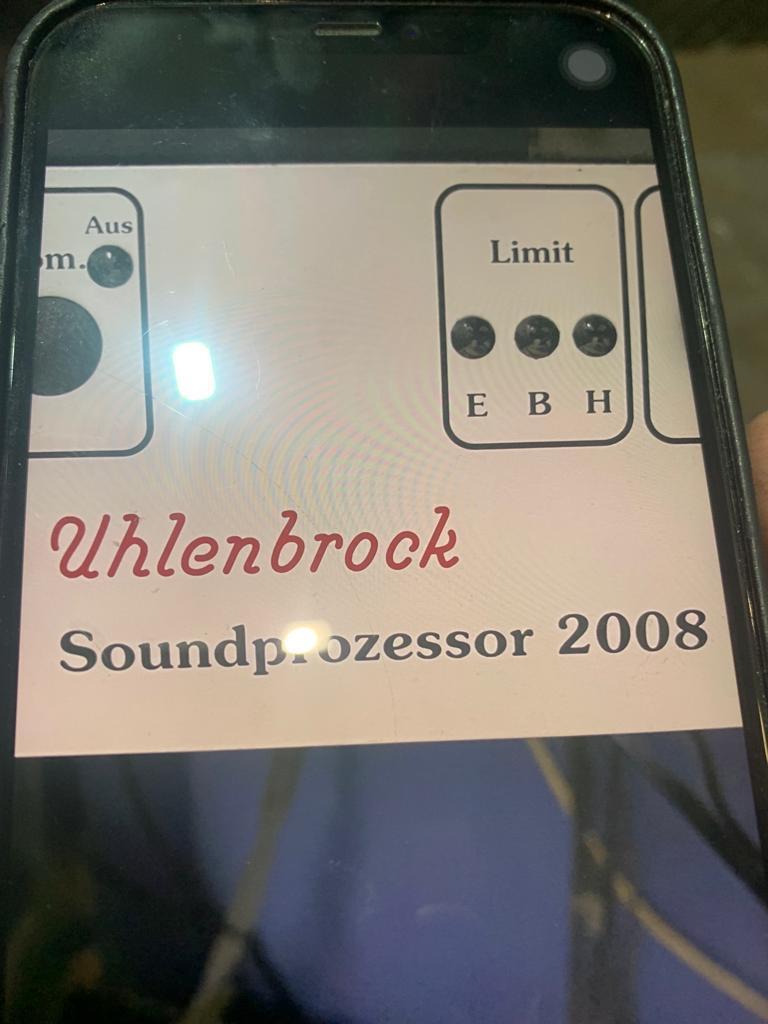
Suche die Schrift von einem Fahrgeschäft (BreakDancer)
ich soll die Frontplatte eines BreakDancers aufarbeiten und kann die Schrift von "Uhlenbrock" nirgends finden.
Ich kann nur vermuten, dass das ganze ca. 2008 entstanden ist.
Ist es überhaupt ein Font oder wurde das damals nur digitalisiert.
Das sieht so aus, als wäre das damals mit der Oberfräse / Graviermaschine von Hand gemacht worden:
Der Schausteller Marco Walz hat sich der Firma Uhlenbrock verschrieben – ich denke, dass er eventuell weiterhelfen kann. Fragen kost’ nix: http://www.walzerfahrt.de/impressum.html